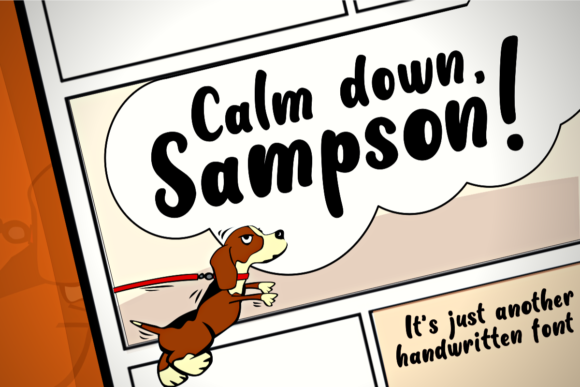
Calm Down Sampson
Calm Down Sampsonのような高品質の素材をお探しの場合、このプレミアムパッケージはクリエイティブなプロジェクトに素晴らしい選択です。
POD(オンデマンド印刷)製品、結婚式の招待状、またはソーシャルメディアのグラフィックを作成している場合でも、Calm Down Sampsonは理想的です。